Sau khi bộ phim “Cô Ba Sài Gòn’ công chiếu, phong cách cổ xưa bỗng trở thành hiện tượng, khơi gợi niềm cảm hứng của những người yêu mến kiểu chữ trên các biển hiệu của Sài Gòn những năm 1950s, 1960s. Cùng An Khánh tham khảo ngay các font chữ Sài Gòn xưa đẹp nhất, được ưa chuộng hàng đầu hiện nay.
Giới thiệu Font chữ Sài Gòn xưa
Font chữ Sài Gòn xưa được lấy ý tưởng từ biển hiệu, tấm pano của Sài Gòn từ những năm 50 – 60 của thế kỷ trước. Thời đó, các tấm biển hiệu này được vẽ hoàn toàn bằng tay và dùng những tấm vải quét sơn.
Nổi lên từ khi xuất hiện trong bộ phim “Cô Ba Sài Gòn”, Font chữ Cô Ba Sài Gòn dành được sự yêu mến của phần lớn những người yêu thích hoài niệm bởi nét riêng trong phong cách retro.
Font Classique Saigon bao gồm tất cả 71 Font Việt hóa từ các Font quốc tế nổi bật như:
- Font Bobel
- Font Parisian
- Font Deftone Stylus
- Font Seaside Resort
- Font Airstream
Những font chữ này phù hợp in trên những tấm áp phích, bảng biểu, thiệp mời, băng rôn, khẩu hiệu, ấn phẩm thiết kế của Việt Nam.
Top 20+ mẫu Font chữ Sài Gòn xưa, Font chữ Retro Việt Hóa đẹp nhất
Font chữ Sài Gòn xưa và font chữ Retro Việt hóa mang đậm tinh thần hoài cổ, lấy cảm hứng từ bảng hiệu, ấn phẩm và quảng cáo những thập niên trước. Các kiểu chữ này thường có nét dày, hình khối rõ ràng, mộc mạc nhưng giàu cảm xúc, rất phù hợp cho thiết kế logo, poster, bao bì và bảng hiệu phong cách vintage. Đặc biệt, font đã Việt hóa giúp hiển thị tiếng Việt chuẩn, dễ dùng trong nhiều dự án thiết kế.
Các Font chữ Sài Gòn xưa đẹp và ấn tượng
Font chữ Sài Gòn xưa gợi sự mộc mạc, hoài cổ, nhưng cũng thể hiện được sự sang trọng và tính nghệ thuật cao.
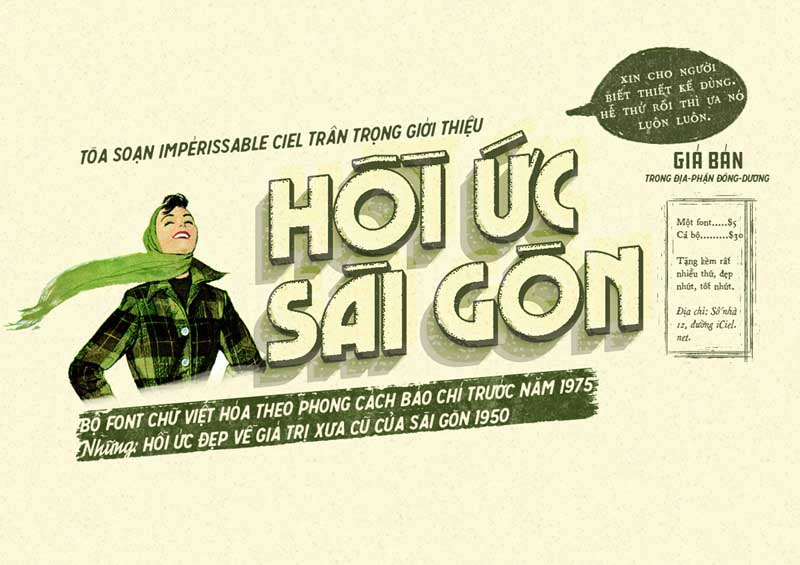
Đây là font chữ được lấy cảm hứng từ phong cách báo chí năm 1975 giúp gợi nhớ về những hồi ức về giá trị xưa cũ của Sài Gòn.
Lấy cảm hứng từ bảng hiệu của những tiệm ảnh cũ, font chữ gợi những hoài niệm cũ với phong cách vintage cổ.
Đây là font chữ có lối thiết kế cách điệu, tone màu gỗ trầm giúp ấn phẩm mang một phong cách đặc biệt hơn.
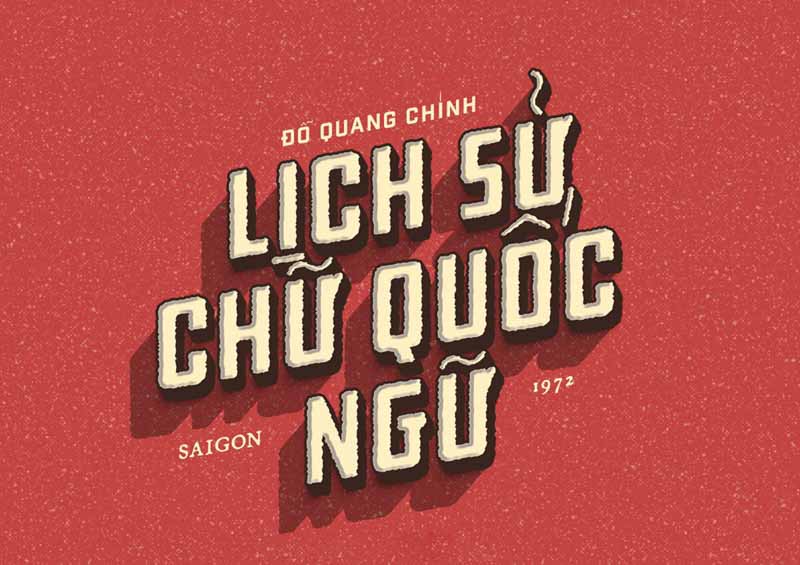
Đây là Font chữ có thiết kế xen lẫn giữa cổ điển và hiện đại
Các Font chữ bảng hiệu xưa
Font chữ bảng hiệu xưa được thiết kế theo phong cách cổ điển, đơn giản, dễ nhìn, bên cạnh đó font chữ này còn thể hiện được sự thanh lịch trong thiết kế.
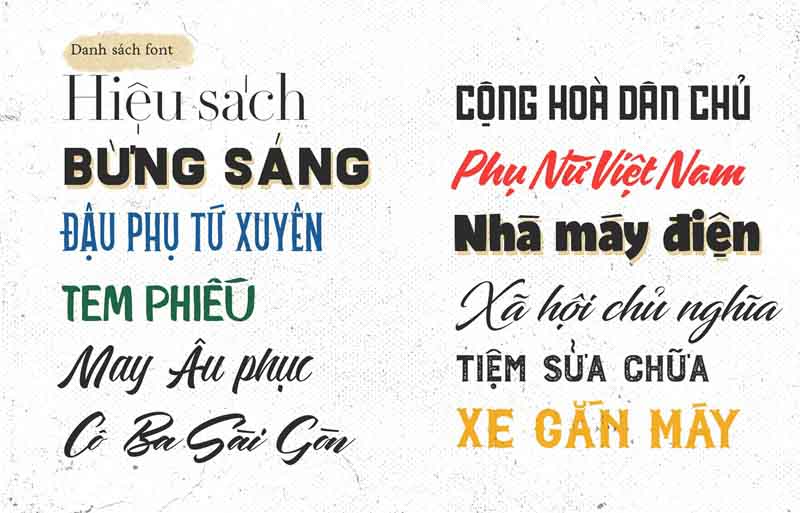
Trên đây tổng hợp những font chữ được cải tiến, cách điệu để phù hợp với từng loại bảng hiệu tương ứng với từng ngành nghề.
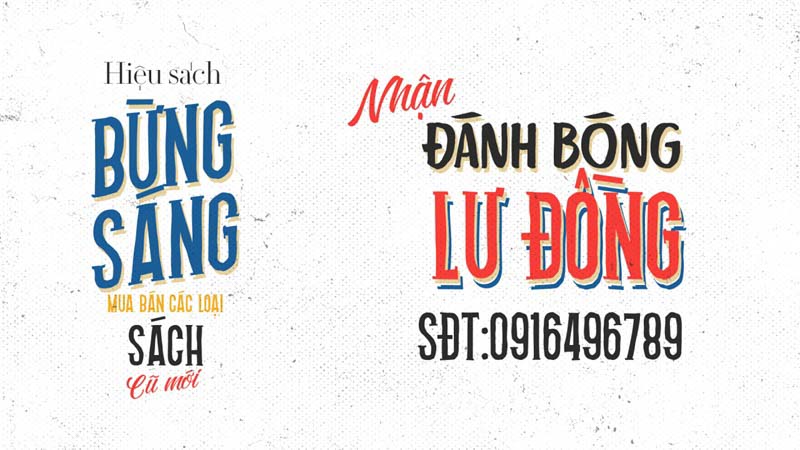
Font chữ mang phong cách phối màu ấn tượng với bố cục tối giản, hài hòa.
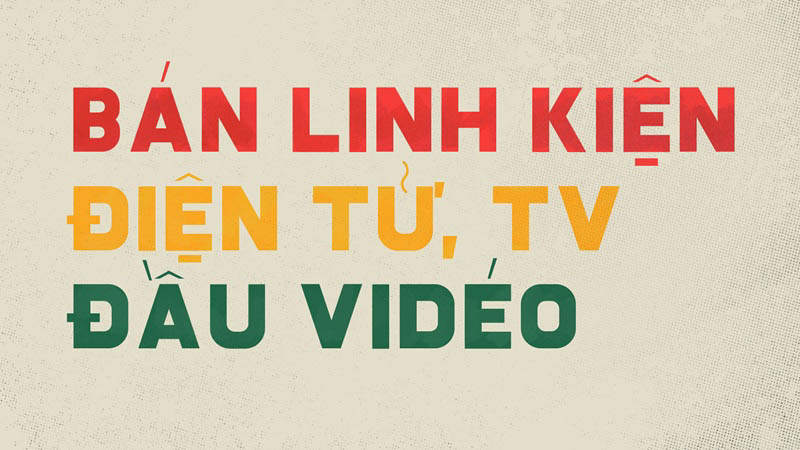
Font chữ tạo điểm nhấn trong cách kết hợp màu với cách đánh dấu chữ ấn tượng.
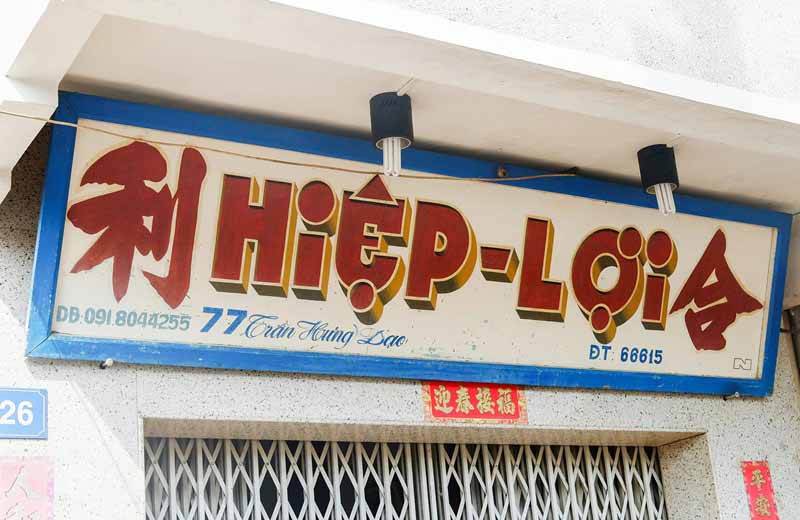
Cách kết hợp chữ nho trong lối thiết kế giúp bảng hiệu gần gũi và đặc biệt hơn.
Các Font chữ vintage việt hóa
Font chữ vintage Việt hóa là nhóm font được thiết kế theo phong cách cổ điển, retro, lấy cảm hứng từ bảng hiệu xưa, báo chí cũ và ấn phẩm truyền thống. Những font này thường có nét chữ dày, bo tròn hoặc hơi thô mộc, mang lại cảm giác hoài niệm, ấm áp và giàu cảm xúc. Việc được Việt hóa đầy đủ giúp font hiển thị tiếng Việt rõ ràng, dễ đọc, phù hợp cho thiết kế logo, poster, bao bì, bảng hiệu và các dự án mang phong cách vintage – retro.
Sự kết hợp hoàn hảo của font chữ viết hoa và viết thường, giúp phong cách thiết kế thể hiện sự sáng tạo của người tạo.
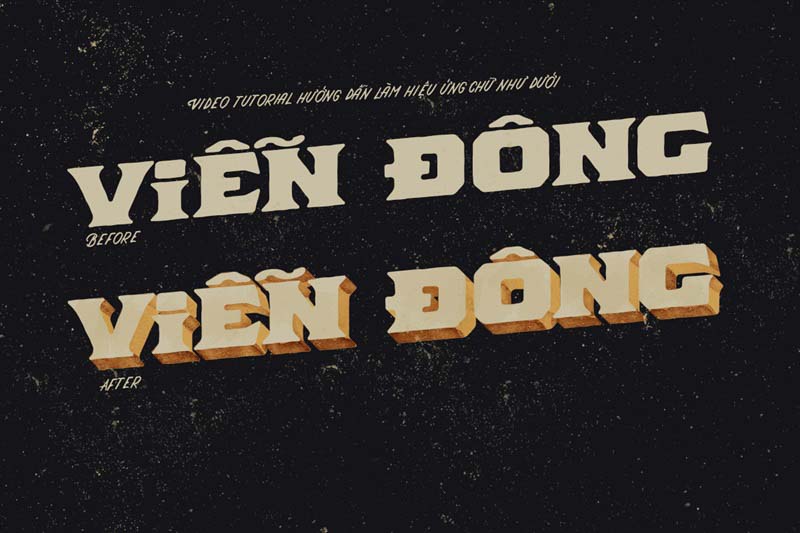
Font có bố cục đối xứng, nổi trên nền đen giúp làm nổi bật tên thương hiệu trên bảng hiệu.
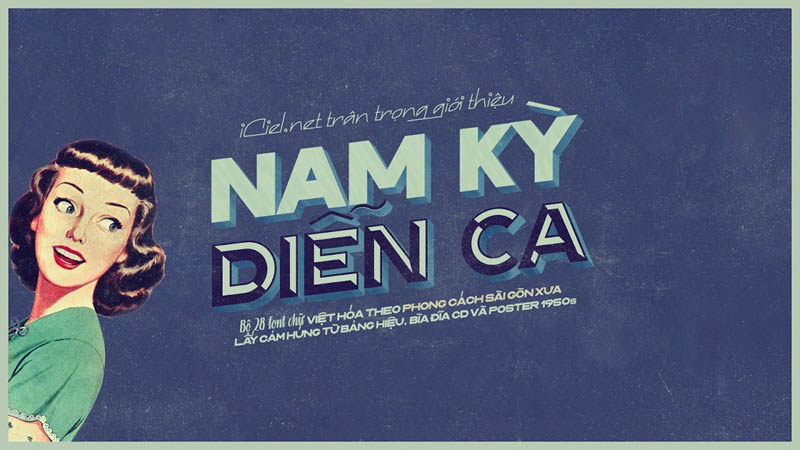
Font chữ nổi bật bởi cách bố trí hoàn hảo giữa text phụ và text chính.
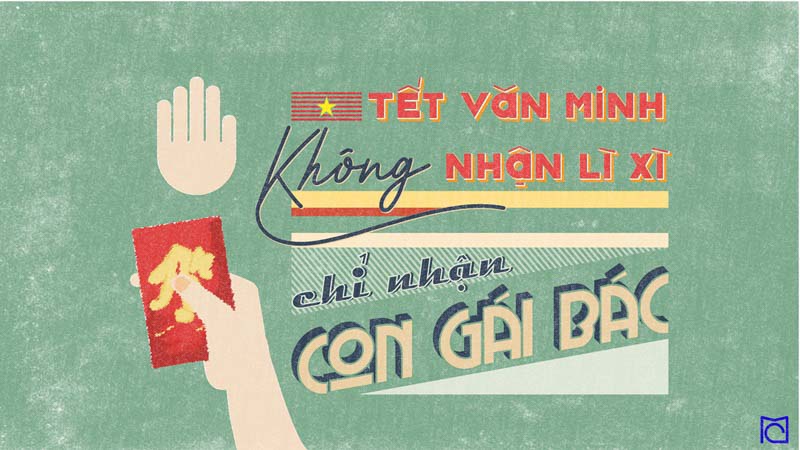
Ý tưởng xuất hiện từ những lời nói hài hước, font chữ được thiết kế cách điệu thể hiện được sự độc đáo trong lối trình bày.
Các Font chữ xưa Việt hóa
Font chữ xưa Việt hóa là những kiểu chữ mang phong cách cổ điển, tái hiện nét đẹp của bảng hiệu, sách báo và ấn phẩm truyền thống ngày trước. Các font này thường có đường nét mộc mạc, hoài niệm, tạo cảm giác gần gũi và giàu chiều sâu cảm xúc. Nhờ được Việt hóa đầy đủ, font chữ xưa giúp hiển thị tiếng Việt rõ ràng, phù hợp cho thiết kế logo, bảng hiệu, poster, bao bì và các ấn phẩm mang phong cách hoài cổ.
Lấy cảm hứng từ những lời ru trong câu ca dao cổ xưa, font chữ mang phong cách tối giản giúp đem đến cho người đọc cảm giác gần gũi.
Xuất hiện trên nền giấy thời bao cấp, font chữ thể hiện được sự tối giản trong phong cách thể hiện.
Lấy cảm hứng từ những dòng chữ trên bảng thông báo năm 1960, font chữ gợi sự cổ xưa, gần gũi với người xem.
Sự kết hợp của nhiều font chữ cổ, phối màu đa dạng giúp bảng hiệu nổi bật hơn từ xa.
Tìm hiểu thêm về Font chữ cùng tác giả – Font L’Hanoienne
Bộ phông L’Hanoienne là kiểu chữ không chân kết hợp cùng độ tương phản nhẹ nhàng, thuộc dự án mới đây của Manh Nguyen. L’Hanoienne mang nhiều đặc điểm giống với người anh em Classique Saigon Font, phù hợp với vẻ đẹp Viễn Đông, dịu dàng, kín đáo của người phụ nữ Bắc Kỳ thế kỷ 20.